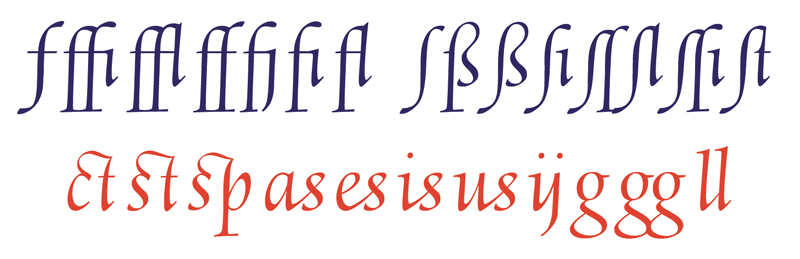
Altes Layout replizieren.
Hallo. Ich suche Ratschläge, wie man Schriftsatz aus Texten der Renaissance am besten nachsetzt (nennt man das so? ich meine replizieren). Und zwar vor allen Dingen die lateinische Schrift mit den damals üblichen Ligaturen -us, -is, ct, ?i, tz, oder auch q in Verbindung mit dem z mit Unterschlinge. Bisher scheitere ich an der mangelnden Unicode-Unterstützung dieser Ligaturen. Möchte das ganze aber dennoch möglichst ohne Kompromisse setzen und dann maschinenlesbar und barrierefrei veröffentlichen. Das letzte Kriterium schließt daher Indesign oder so etwas aus, da das nicht barrierefrei ist. Dank Unicode, die sich weigern Lösungen für Ligaturen zu implementieren :-( bin ich wohl zu einem Workaround gezwungen. Meine bisherigen Erwägungen:
1. Ich setze es in HTML mit einem Spezialfont (welchen kann man dazu nehmen) und lade den Font via @font-face.
2. Ich setze es in Word, exportiere nach PDF und integriere einen Spezialfont in die PDF.
Meine Fragen: Welche Schriftart könnte man nehmen? (siehe im Anhang den Original-Druck)? Oder könnt ihr mir vielleicht zu einem anderen Lösungsweg raten? fontlz.jpg
Schau Dich mal auf der Seite der Medieval Unicode Font Initiative um: http://www.mufi.info/. Die MUFI erarbeitet Empfehlungen, die allgemein anerkannt sind, für die PUA-Codierung von Zeichen, die im Unicode (noch) nicht enthalten sind. Einige Zeichen wurden auch schon aus der MUFI-Empfehlung in den Unicode übernommen. Auf der Seite sind einige Schriften aufgeführt, die MUFI-Zeichen enthalten, darunter zum Beispiel eine kostenlose Fassung der Andron.
Damit könntest Du also die nötigen Zeichen Unicode-codiert in Deinen Text einfügen, und am Ende eine PDF-Datei draus erzeugen, um sicherzugehen, daß der Text mit einer Schrift dargestellt wird, die die benützten Zeichen enthält. Es wäre gleich ob Du dafür InDesign, Word oder ein anderes Programm benützt.
Hallo. Ja, kenne MUFI und benutze auch einen MUFI-Font (LeedsUni). Ich habe mich mal durch die 245-seitige Empfehlung der MUFI gewühlt, da gibt es ja die merkwürdigsten Zeichen, doch eine is- oder us-Ligatur habe ich vergebens gesucht, dabei ist sie doch gängig in allen Druckerzeugnissen auf dieser Zeit?
Meine demnächst (wirklich!) erscheinende Tierra Nueva hat lateinische Abkürzungsligaturen für "per" (p mit Querbalken) und "qe" (q3), ziemlich viele langs-Ligaturen, etc., aber auch keine us- oder is-Ligaturen.
Außerdem ist die Anmutung weniger "sanft", da Kupferstecher-Werkzeugen nachempfunden, nicht mit Stempeln gedruckt.
Hallo Herr Nagel, ich habe noch einmal nachgeschaut, soweit ich das sehe erscheinen die us- und is-Ligaturen im mir vorliegenden Druck ausschließlich in der Kursive! Sie weichen in der Form auch von dem von Ihnen geposteten Abbild ab. Hier ein Beispiel usis.jpg MUFI kennt diese Ligaturen also nicht?
Ich kann mich auch nicht erinnern, so einen Verbund schon mal in einer Starrschrift (aufrechten Antiqua) gesehen zu haben. Hast Du die auf der MUFI-Seite angebotenen Schriften alle durchgesehen? Falls keine der Schriften die Verbünde enthält, dann vielleicht eine der Andron-Fassungen. Die umfangreichste Fassung (Andron Mega) kostet allerdings 390 € …
Hallo, deine nette Idee war ja “prä-offizielle Code-Stellen” zu finden, die womöglich künftig offizieller Unicode-Standard werden. Leider finde ich mich auf der MUFI-Seite nicht so gut zurecht, gibt es da eine Art Übersicht oder Such-Funktion für Glyphen? Wie suche ich auf der MUFI-Seite nach einer us- oder is-Ligatur?
da die -us- und -is-ligaturen kein standard sind, benötigst du wohl eine schrift, die von jemandem inspiriert worden ist, der jene ligaturen verwendete. wenn du dir stephanus-ausgaben anschaust, wirst du unendliche ligaturen (ca. 300 meinte mein prof) finden, die zum teil recht willkürlich eingesetzt werden (und, der alptraum eines jeden studenten, in früheren handschriften sogar wortgrenzen überbrücken).
Mag sein, aber us- und is-Ligatur (in der Kursive) ist gang und gäbe in den Drucken aus dieser Zeit. Hier handelt es sich weder um Willkür, noch um irgendein Kuriosum. Von daher bin ich von MUFI enttäuscht!
was ziemlich albern ist, da die Medieval Unicode Font Initiative kaum renaissance-zeichen berücksichtigen muss, gelle? ;)
“Albern” nicht, aber vielleicht hatte ich eine falsche Erwartung.
Die Frage ist, ob sowas überhaupt in den Unicode kommen könnte bzw. muss.
Tragen diese Ligaturen eine eigene Bedeutung, oder sind sie "bloß" eine spezielle Darstellungsform von u+s bzw. i+s?
Wikipedia: Unicode ist ein internationaler Standard, in dem langfristig für jedes sinntragende Schriftzeichen oder Textelement aller bekannten Schriftkulturen und Zeichensysteme ein digitaler Code festgelegt wird.
Ich freue mich über die guten Beiträge. Um auf ihre Frage einzugehen, Herr Nagel: meine Auffassung von “sinntragend” ist schon eher wenig tolerant, und ich sehe bspw. die von mir gewünschte us-Ligatur durchaus als reine Darstellungsform ohne sinntragende Funktion. Aber ich denke wir (als Schriftsetzer und Ästheten) sind uns alle einig, daß offene Standards auch für “sinnfreie” (semantisch unerhebliche) Darstellungsformen durchaus nötig sind und fehlen, Unicode hin, Unicode her. Und um nochmal kurz zusammenzufassen: Unicode erklärt sich nicht bereit, solche Standards zu setzen, da sie sich auf die funktionale (semantische) Ebene beschränken möchten. Wäre da nun nicht das W3C gefordert, sich um solche Standards im Bereich der Formatierung und Darstellungform zu kümmern? Doch seit Jahren passiert in dieser Hinsicht nicht viel und HTML ist für Gestaltung nach wie vor ein Graus, es wirkt auf mich nicht durchdacht, nicht benutzerfreundlich, und hinderlich für jedes Layout, was über die primitivste Erscheinung hinausgeht. Doch wie löse ich jetzt konkret mein Problem? Der Zero Width Joiner wird soweit ich weiß von keinem Browser so interpretiert, daß er zu Ligaturen führt. Mir bleibt wohl vorerst nichts anderes übrig, als einen Font zu suchen, der über alle von mir benötigten Ligaturen und sonstigen Sonderzeichen verfügt, und dann vorbei an jedem Standard in HTML (vielleicht mit @font-face) oder PDF zu wursteln. Barrierefreiheit ist für mich ganz wesentlich.